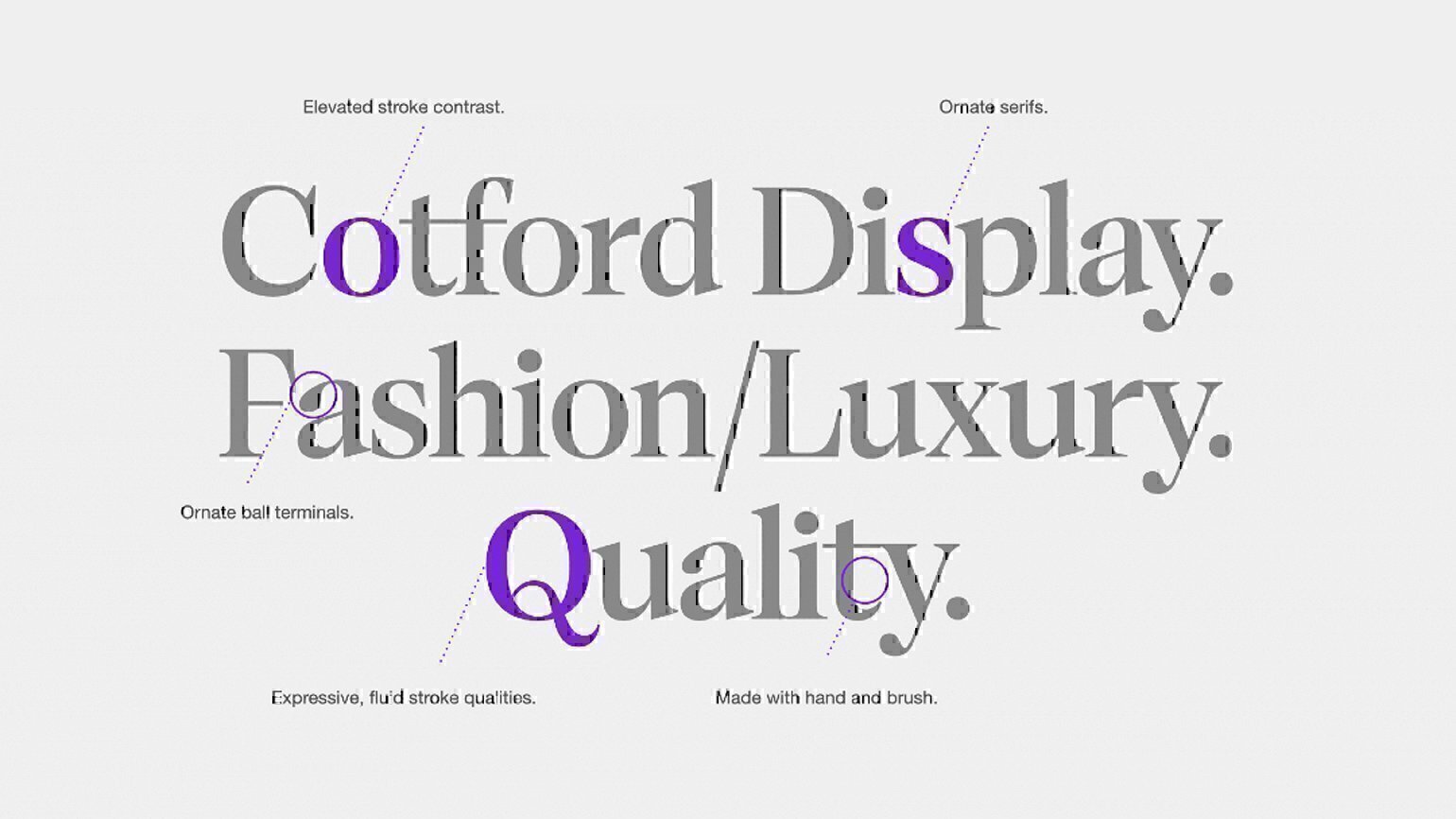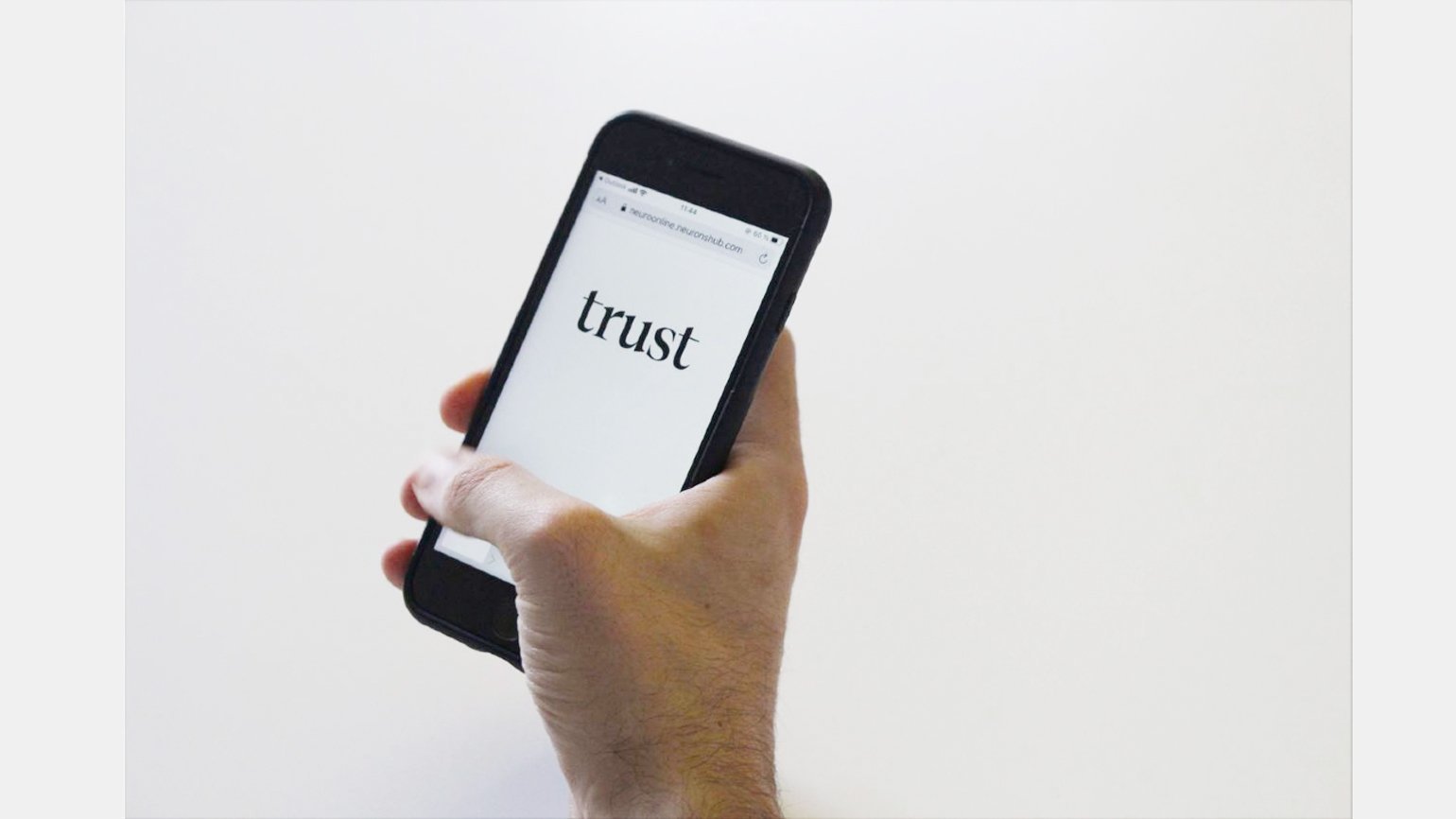
Компания Monotype выяснила, как шрифты влияют на эмоции людей
Правильный выбор шрифта помогает укрепить доверие между брендом и потребителем.
Шрифтовая компания Monotype и фирма Neurons, занимающаяся прикладными исследованиями в области нейробиологии, провели совместное исследование. Они выяснили, что дизайнеры поступают правильно, когда тщательно и долго подбирают идеальный шрифт для своего проекта.
Компании провели опрос среди 400 респондентов. Им предлагалась взглянуть на одни и те же слова, написанные разными шрифтами — изысканным шрифтом с засечками Cotford, гуманистическим гротеском FS Jack и геометрическим гротеском Gilroy. Эти шрифты выбрали из-за их сходства с теми, которые используют настоящие бренды. Но Monotype и Neurons воздерживались от упоминания реальных компаний, чтобы не искажать ассоциации респондентов. Среди слов были такие, как «качество», «доверие» и «инновация». Их просили оценить эти надписи по таким показателям, как, например, искренность и достоверность.
Результаты подтвердили гипотезу о том, что шрифты влияют на эмоциональное восприятие бренда, а также на впечатления и чувства людей. Элегантный шрифт Cotford ассоциировали с качеством — такие часто используют для продвижения предметов роскоши. Гуманистический шрифт без засечек, FS Jack Regular, ассоциировался с инновациями и доверием. А геометрический шрифт без засечек Gilroy Bold связывали с честностью и аутентичностью. Его часто используют в рекламе товаров для быта.
Получается, что шрифты действительно влияют на реакцию потребителей на слоганы и лозунги, а ещё побуждают воспринимать логотип компании в более позитивном ключе и укреплять доверие между брендом и потребителями.
«Мы только задели поверхность. Ширина и глубина возможностей тестирования того влияния на эмоции, которое оказывает шрифт, огромны, и мы хотели бы продолжать делиться этим с вами по мере того, как мы открываем больше и больше», — заявил Джеймс Фукс-Бейл, старший директор по бренду Monotype.